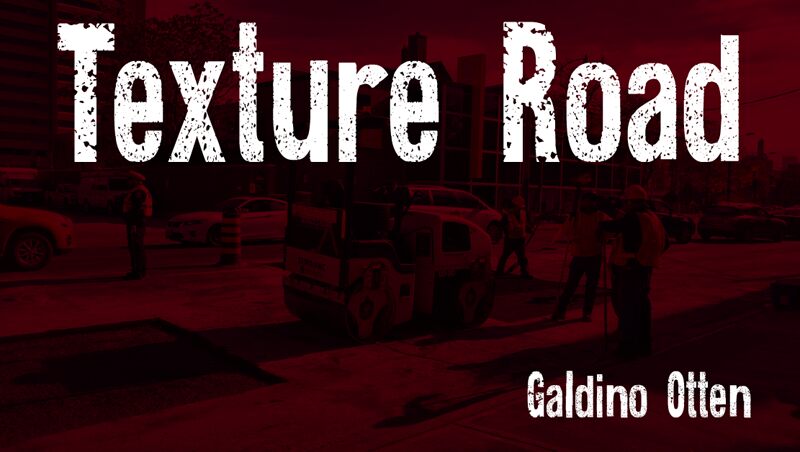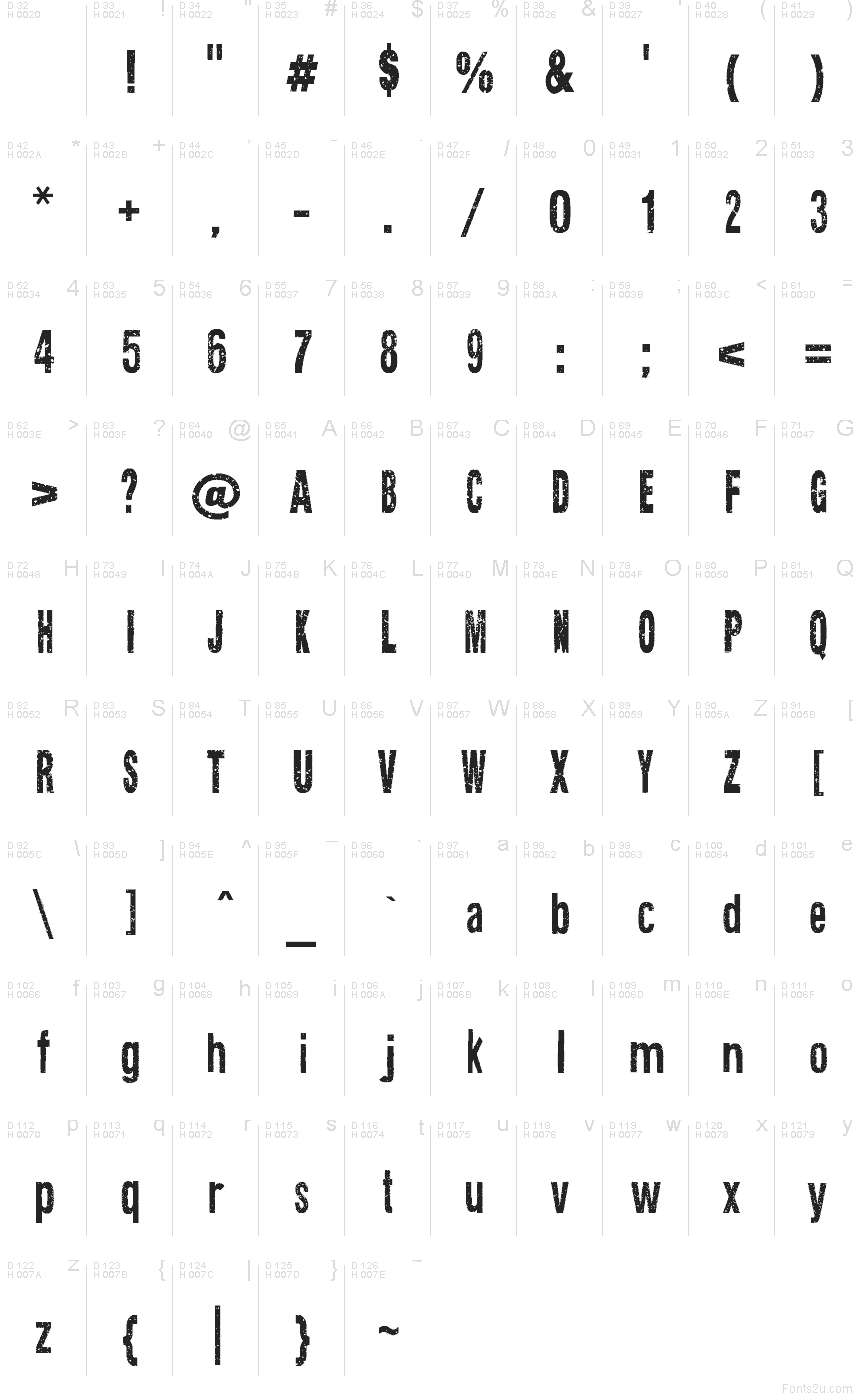
Texture Road od Galdino Otten Fonts je bezplatné zvětralé nadpisové písmo s vysokými, hustě uspořádanými písmeny bez paty. Jeho husté tahy jsou všude oštípané a odřené, což vytváří drsný povrch připomínající opotřebovaný inkoust nebo zvětralý potisk u silnice.
Grunge vliv se hodí k hudebním plakátům, skate merchandise a obálkám nezávislých časopisů. V těchto kontextech umožňují opakované skvrny a chybějící kousky, aby písmo fungovalo spíše jako součást vytištěné textury než jako čistý nápis.